第13回 圧巻の200冊、祖父江慎+cozfish展
ggg 第234回企画展 「祖父江慎+cozfish展」
2005年11月4日(金)~11月26日(土) ギンザ・グラフィック・ギャラリー(ggg)
2005年11月4日から26日まで、ギンザ・グラフィック・ギャラリー(ggg)では、第234回企画展「祖父江慎+cozfish展」が開催されています。
祖父江さんといえば、書店でひときわ目を惹くブックデザインでおなじみですが、今まで1300点もの本を手がけたそうです。本展ではそのうちおよそ200冊が展示されています。
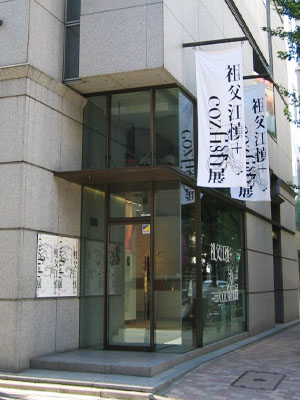
この中が「うっとり」パワーのるつぼです
1Fの展示
扉を開けると、「ヤットコスットン、チョイナチョイナ~」と子どもたちの声で繰り返される何やら不思議な曲が流れています。そして目の前には……
あっ、かわうそくん!
吉田戦車『伝染るんです』コミックス第1巻(小学館)が大きな布の本になって垂れ下がっています。ということは、会場に流れる不思議な曲は『伝染るんです』第2巻に楽譜が載っている「かわうそ音頭」ですね。
『伝染るんです』第1巻といえば、半ば伝説と化した造本で有名です。版面が曲がって印刷されていたり、突然違う紙が混ざっていたり、通常は最後のページにくる奥付のページ位置が間違っていたり、帯がまがって切れていたり、カバーのそで(折られた部分)の長さが違っていたり、ページのサイズが違っていて飛び出ていたり……と挙げればきりがありません。「第1巻なので著者も編集者もみな慣れておらず間違った本造りをしてしまった」という設定でデザインされたそうです。ちなみに第2巻は、「1巻の失敗をやりなおした」本がデザインされています。
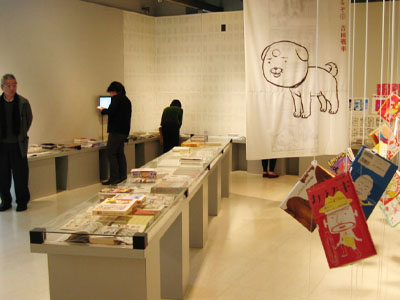
書店で見たことがある本がたくさん並びます
1Fの展示では、造本上、非常に手間のかかった本や、祖父江さんのブックデザインといえばこの方、という作家の作品が並びます。
ほぼ日刊イトイ新聞の人気企画を単行本化した『言いまつがい』(東京糸井重里事務所)の単行本は、そのタイトルどおり「まつがった」造本*1。だいたい四角い形をわざわざ作っているので、本を立てるとなんだか傾いています。
言いまつがい
花村萬月『浄夜』(双葉社)は、手にとるとカバーの紙の手触りが印象的な一冊です。表側が白い網の目のようなものにびっしり覆われているんですが、網目の印刷につかった版を実際に見ることができます。
浄夜
書籍を印刷するにあたっての、印刷現場への指示も見ることができます。ふだんは出版社や印刷会社しか見ることができないものです。写真は楳図かずお『おろち』第3巻の指示で、「印圧強め+インキモリモリで刷ってください!」とあります。
『楳図PERFECTION!』シリーズでは、背の著者名やタイトルで秀英5号かなが使用されています。
インキモリモリで!
矢沢あい『ご近所物語 完全版』(集英社)のカバーには、ファッションデザイナーを目指す主人公・実果子のブランド「HAPPY BERRY」のロゴがエンボス加工されています。
ハッピーベリーのロゴ
祖父江さんの大学時代の先輩でもあるしりあがり寿『瀕死のエッセイスト』(角川書店)の設計書です。本の内側・外側、カバーに使用するイラストなど事細かなアイデアが記してあって、つい読みふけってしまいます。
死ニカケ瀕死のエッセイスト
壁際には、本が紐でぶら下げてあります。直接手にとって、じっくりながめることができます。カバー裏や小口などふだんは気にも止めないようなところに意外なしかけがあったりしますよ。吉田戦車・しりあがり寿・中川いさみら祖父江さんがたくさんブックデザインを手がけている作家の作品がまとまっています。
直接手にとってじっくりながめてください
階段の展示
それでは地下の展示室に向ってみましょう……あら?
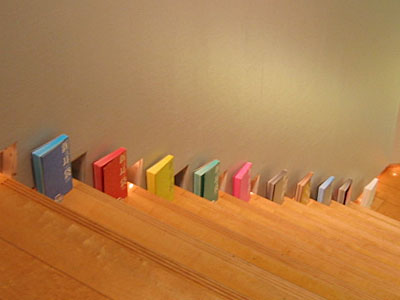
階段に……?
階段にも本が並んでいます。1冊に99の怪談を収録した、木原浩勝・中山市朗『新耳袋』シリーズ(メディアファクトリー)です。
階段に怪談
地下展示室でまず目に飛び込んでくるのが、シリーズでブックデザインを手がけている新書「よりみちパン!セ」(理論社)のコーナーです。100%ORANGEのイラストや書籍の版面をオーバーラップさせた映像にもご注目下さい。
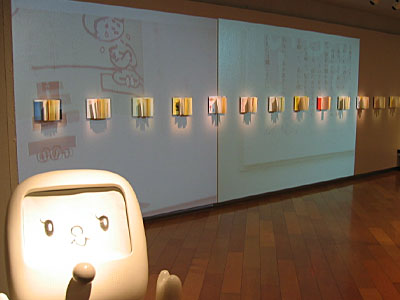
よりみちパン!セ
よりみちパン!セはそれぞれのテーマと著者の組み合わせが意欲的で、創刊以来話題のシリーズです。それぞれの本で異なるカバーや見返しなどを見比べることができます。
悩めるヤングたちに「個性ハ必要ナシ」とオヤジ的生き方を指南する、しりあがり寿+祖父江慎『オヤジ国憲法でいこう!』も、今年7月にシリーズの1冊として刊行されました。
見返しのイラストもみんな違いますよ
地下には写真集や雑誌のブックデザインなども並んでいます。
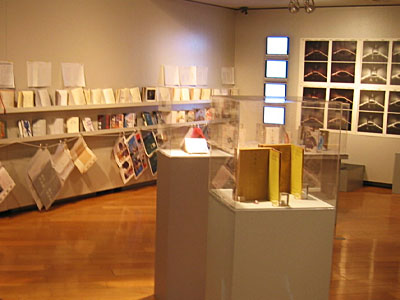
地下の展示
執筆陣の豪華さもさることながら、函入り・クロス装や本文の精興社明朝など手をかけた丁寧な造本で大人の心もつかんでしまった「ミステリーランド」シリーズ(講談社)。秀英体がタイトルに使われているものもありますよ。
手前にあるのは「ターシャ・テューダー・クラシックコレクション」シリーズ(メディアファクトリー)です。アメリカを代表する絵本作家ターシャ・テューダーの作品の復刻シリーズですが、ターシャ・テューダーの優しい雰囲気がブックデザインにもそのまま反映されています。
どちらも長く大切にしたくなる造本です
壁にはずらりと本が並んでいます。本だけではなく、造本設計書、書籍、そのカバー、そして色校正紙の順に並んでいます。
こうして一度に眺めると、祖父江慎+cozfishのデザインの多様さに驚くばかりです。
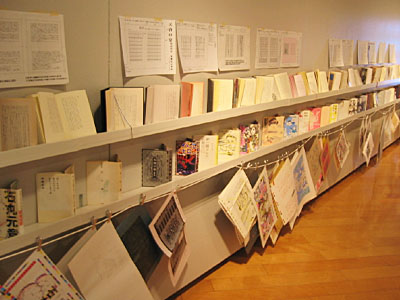
圧巻のボリューム
中原昌也『ボクのブンブン分泌業』(太田出版)では、タイトルや写真のような見出し部分に秀英三号かなが使われています。
ボクのブンブン分泌業
高橋源一郎『ミヤザワケンジ・グレーテストヒッツ』(集英社)の本文は、つながった「い」でおなじみの秀英細明朝体でした。
ミヤザワケンジ・グレーテストヒッツ(の版面)
個人的にとても気になったのがこちらです。岡野玲子・夢枕獏原作『陰陽師』(白泉社)は、祖父江さん手書きの風水盤の上に、コミックスが並べられています。
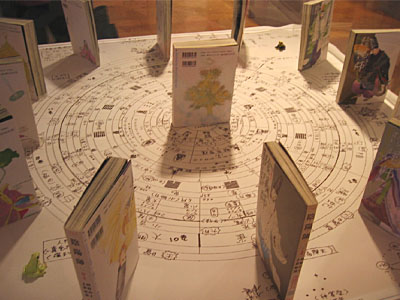
手書き風水盤の上にならぶ『陰陽師』
こちらはブラックライトのコーナーです。蛍光インキをつかったカバーが、ライトを当てられて光を放っています。
本の色々なところが光ってます
1Fの『伝染るんです』と同じように、地下も京極夏彦『どすこい(仮)』(集英社)と恩田陸『ユージニア』(角川書店)が大きな布の本になっています。写真はそば展示されている『どすこい(仮)』の設計書です。手書きの指定と実際の結果を見比べることができます。
細かい指定をみることが出来ます
ブラックライトコーナーの脇に、階段に展示してある『新耳袋』のカバーが広げてあり、傍らに虫めがねが置いてあります。のぞいてみると、小さな文字で文章が印刷してあります。これは単なる飾りではなく、カバーに全本文が印刷されているそうです!
そして多くの怪談を収録した『新耳袋』には、普段は目にしないとあるところに、魔よけがすられているそうです……。
カバーだけで全部読めるそうです
というわけで、祖父江慎+cozfish展をかけあしでご紹介しました。これほどまでバラエティに富んだブックデザインを可能にするには、多岐にわたる印刷・製本の技術に対し、非常に深い知識をお持ちなのがわかります。
約200点もの本が一同に会しているので、ここでご紹介したのはほんの一部です。秀英体が使われた本もたくさんあります!
見たことのある本が必ず見つかるはずです。ぜひ会場に足をお運びください。
- *1 『言いまつがい』のブックデザインについては、ほぼ日刊イトイ新聞「『言いまつがい』装丁伝説!あのへんな本をつくった人たち。」で詳しく紹介されています。